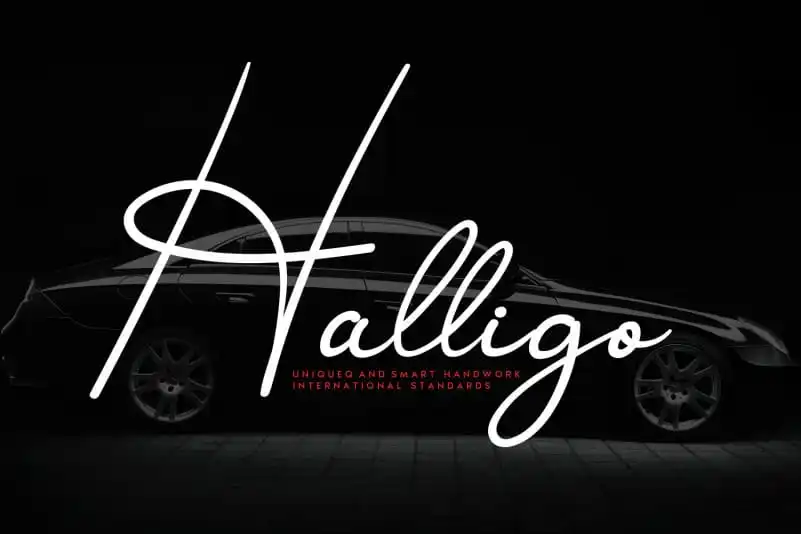
Halligo Handwritten Font – Fonte Grátis
Halligo Handwritten Font
Na categoria das fóntes escritas a mão, está Halligo Handwritten Font, um produto criativamente especial que destaca-se entre as demais. Escrevemos sobre esta fonte com um tom informativo e convidativo para que você possa apreciar seus detalhes únicos em projetos gráficos. Inspirada por texturas de escrita natural e emotiva, Halligo captura a essência do estilo a mão, fornecendo uma experiência visual envolvente e natural. Este recurso adicional traz mais vida à sua identidade visual, permitindo um toque personalizado em qualquer projeto. Com Halligo Handwritten Font, deixe seu trabalho se destacar com elegância, sensibilidade e originalidade.